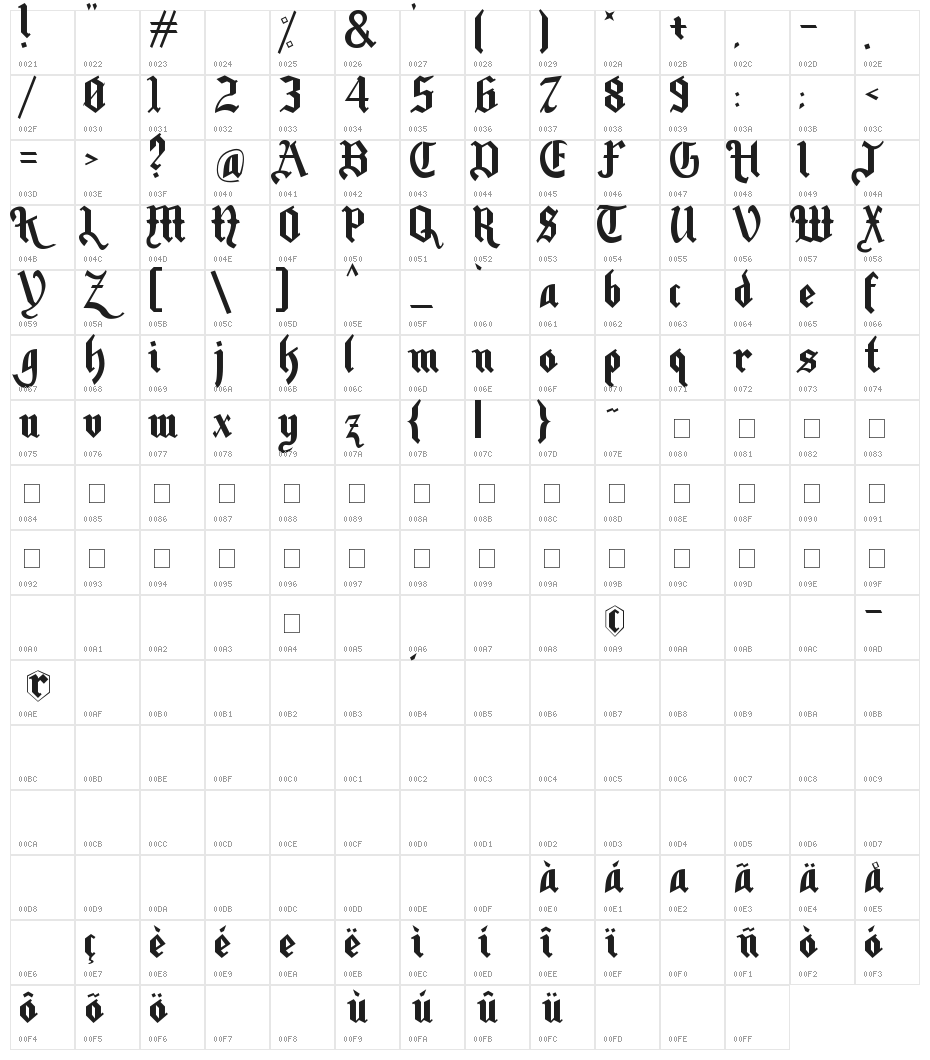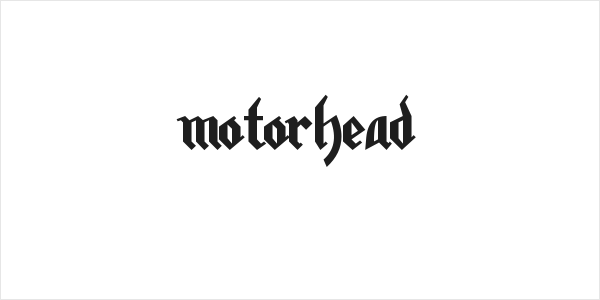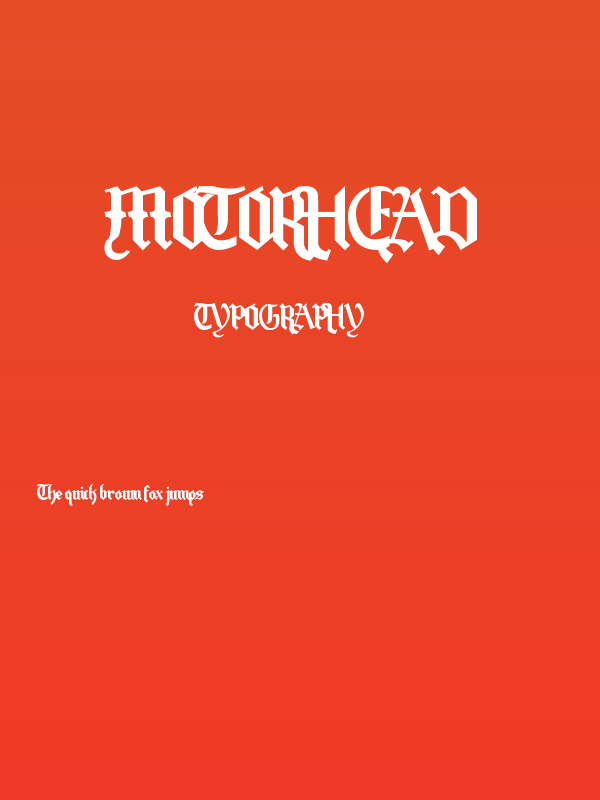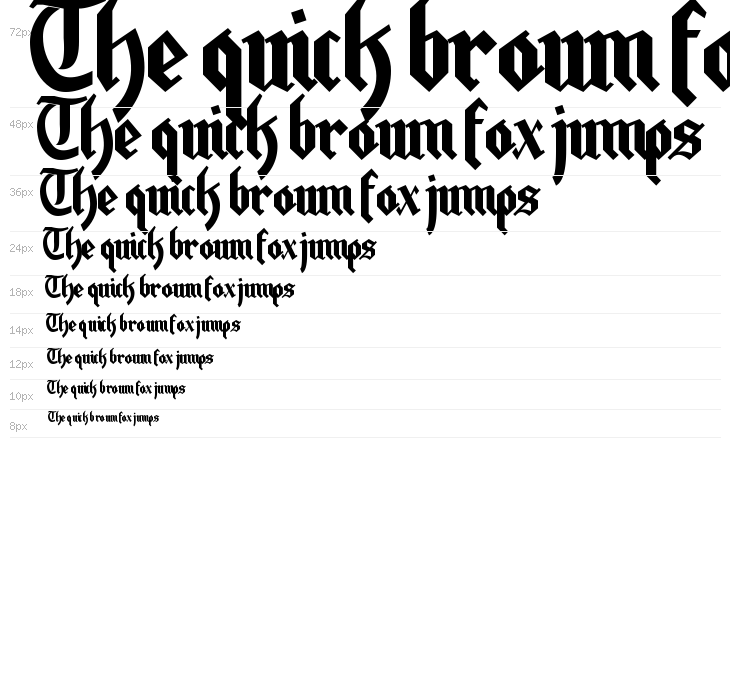
motorhead Font
✎ Gothic
| श्रेणियाँ | Gothic |
| कंट्रास्ट | High |
| समग्र शैली | Classic |
| उपयोग का मामला | Headlines, Logos |
| सुझाए गए प्रोजेक्ट | Ideal for event posters, album covers, luxury branding, and historical-themed designs. |